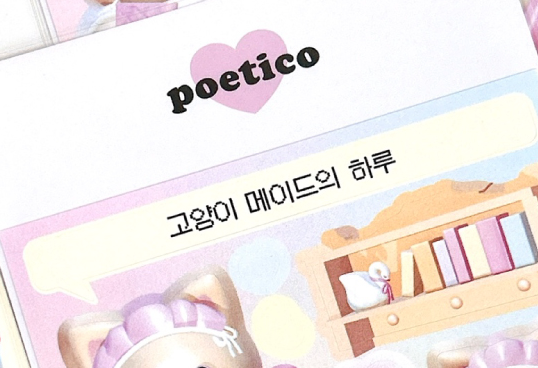
이 서체 알 수 있을 까요? min*** 2023.12.09 픽셀같은데 산돌에는 없네요 혹시 아실까요? 댓글 0 등록 sha*** https://noonnu.cc/font_page/801 '갈무리11'입니다 2023-12-13 답글 달기 댓글 더보기 쉽고 빠르게 가장 비슷한 폰트를 알고 싶다면? 이미지로 검색하기
https://noonnu.cc/font_page/801 '갈무리11'입니다